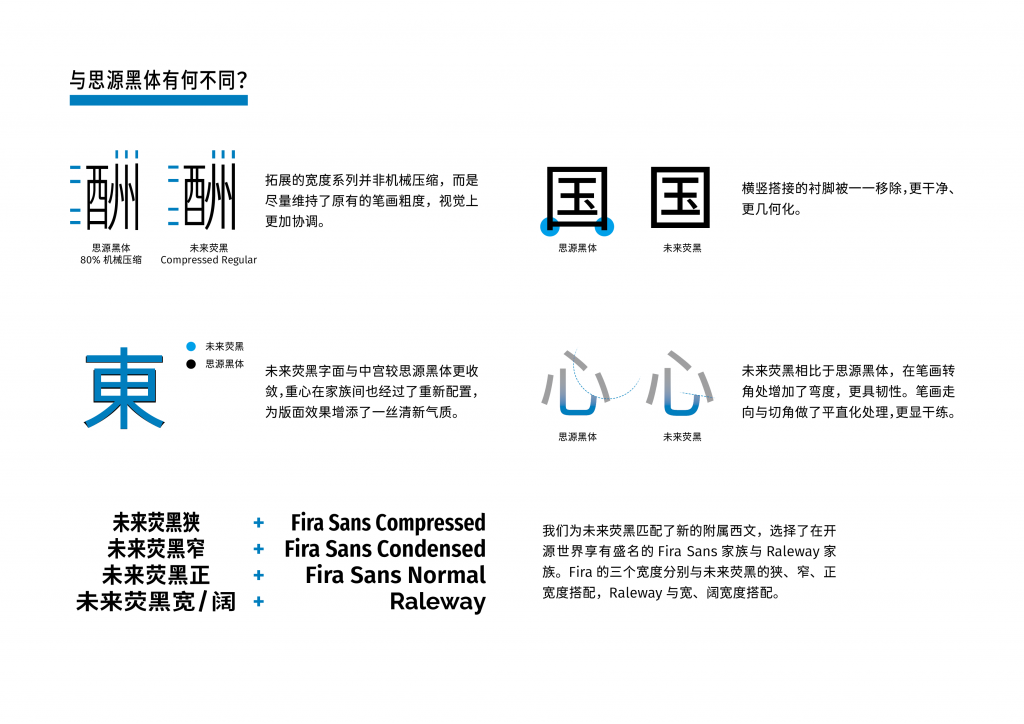
未来荧黑是一个基于思源黑体、Fira Sans和Raleway的开源字体项目,支持简体中文、繁体中文与日文;思源黑体的7字重被扩展为9字重,并提供了宽度系列,全家族共44款字体。
相比于思源黑体,未来荧黑的造型更加简明现代,版面效果清新轻快。未来荧黑的中宫与字面更加收敛,重心在字重之间经过了重新配置;笔画细节上处理得更加干练,简洁而平直化。您可以下载样张来预览未来荧黑的设计。
未来荧黑的实现介于参数化与轮廓滤镜,使用了图像处理算法对字形建模。字体的制作并没有借助字体设计软件,而是用一个Web实现的可视化调参工具来确定字体参数。